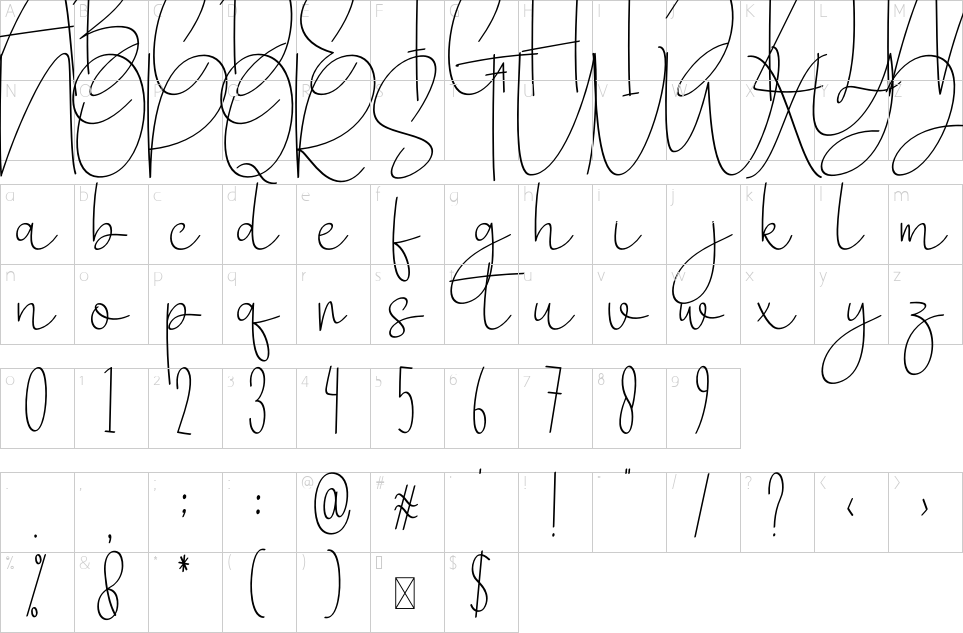
A fonte ‘Santa Signature’ é uma escolha perfeita para personalizar sua apresentação de PowerPoint, criar cartões de aniversário, ou simplesmente adicionar um toque de personalidade a qualquer tipo de projeto visual. Desenvolvida pelo designer desconhecido, a ‘Santa Signature’ apresenta um estilo elegante e criativo que certamente dará um toque agradável aos seus materiais. Com uma simplicidade que se torna sofisticada, esta fonte é ideal para criar mensagens de aniversário românticas, cartas de agradecimento ou até mesmo gráficos de e-mail. Com apenas 325 downloads, a ‘Santa Signature’ demonstra o apreço e a qualidade que esta font oferece. E como a ‘Santa Signature’ é uma fonte gratuita, você pode experimentar e explorar suas possibilidades sem limitações. Não perca a chance de dar um toque especial a seu trabalho com esta fonte única e elegante.